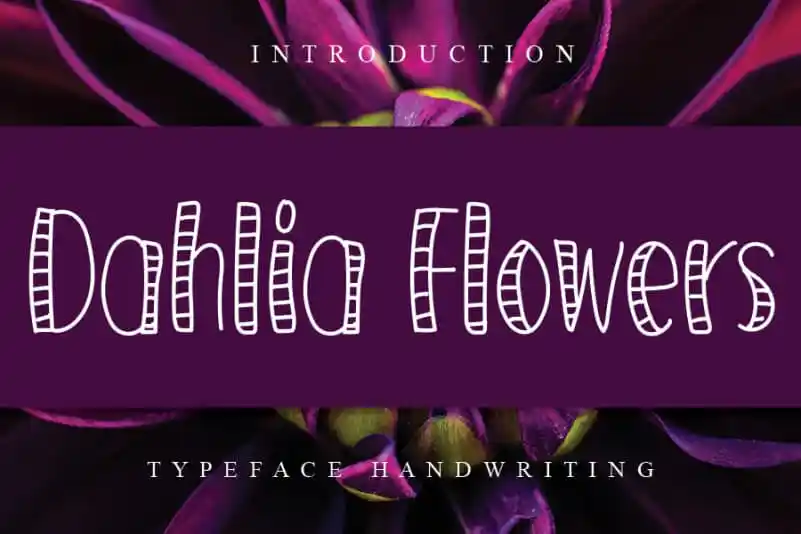
Dahlia Flowers Display Font – Download Grátis
A fonte ‘Dahlia Flowers Display Font’ é uma escolha natural para quem busca alegria e simplicidade no design. Com seu estilo único e natural, esta fonte se adapta perfeitamente a um vasto leque de projetos, limitado apenas pela imaginação do criador. É ideal para aplicativos como cartões de aniversário, adesivos ou até mesmo títulos em livros infantis, onde sua proposta de ser amigável e descontraída será bem recebida. Englobando uma grande variedade de estilos e cores, a ‘Dahlia Flowers Display Font’ surge como um atalho perfeito para aqueles desejando incorporar nuances leves de natureza em seus projetos visuais. Simples, versátil e encantadoramente única, ela se torna uma fonte que merece espaço na sua coleção de recursos gráficos.